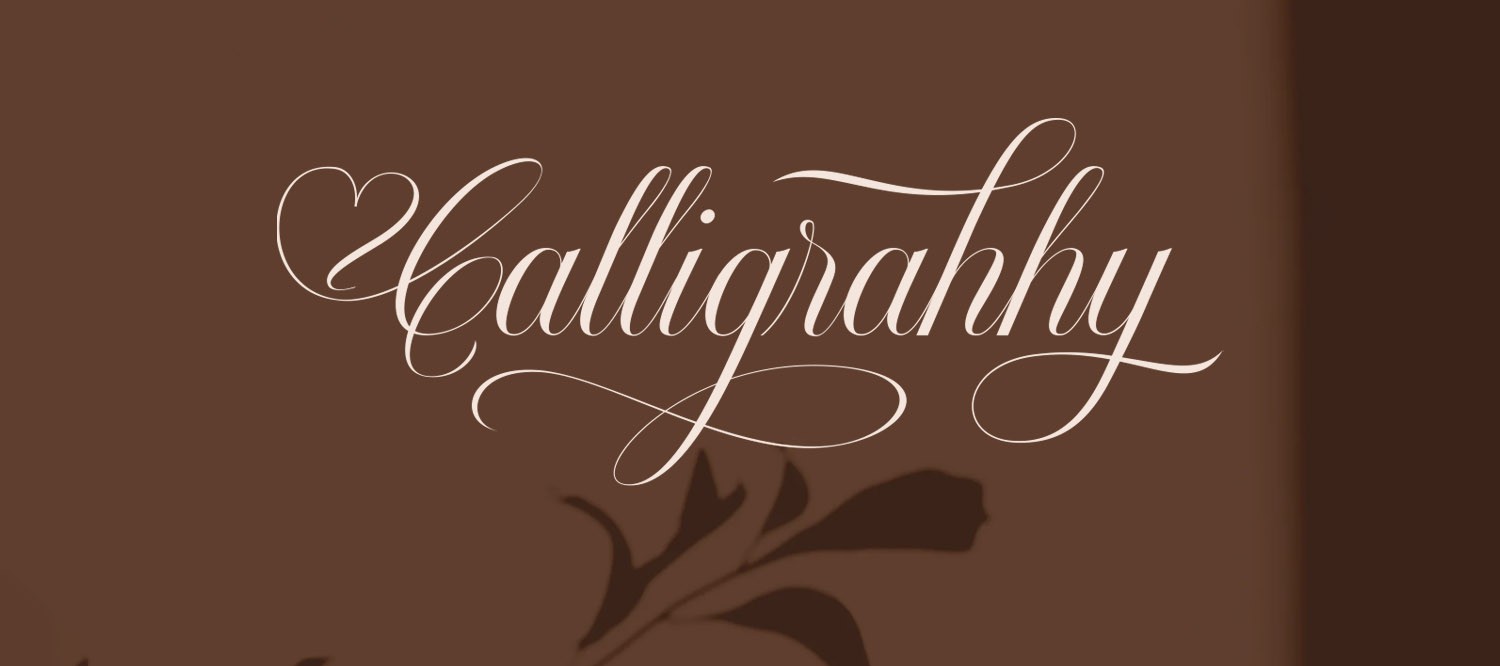
[Tải xuống] TOP 12+ font chữ calligraphy việt hóa mới nhất 2025
Trong lĩnh vực thiết kế, việc lựa chọn font chữ phù hợp đóng vai trò cực kỳ quan trọng trong việc thể hiện phong cách và cá tính của dự án. Font chữ Calligraphy, với nét chữ uốn lượn mềm mại, thanh thoát, là lựa chọn hoàn hảo cho những dự án cần sự tinh tế, trang nhã. Bài viết này sẽ giới thiệu đến bạn những font chữ Calligraphy đẹp mắt, phù hợp cho các dự án như thiệp cưới, thiệp mời, hay các ấn phẩm thiết kế sang trọng.
Font chữ Calligraphy là gì?
Font chữ Calligraphy (hay còn gọi là font chữ thư pháp) là một kiểu chữ được thiết kế để mô phỏng hoặc lấy cảm hứng từ các nét viết tay nghệ thuật, có sự uốn lượn và biến đổi mềm mại, linh hoạt của các nét chữ. Đây là một phong cách chữ truyền thống được dùng trong thư pháp, nơi người viết sử dụng bút lông hoặc bút chì mềm để tạo ra các chữ cái có độ dày mỏng khác nhau, mang tính thẩm mỹ cao và đầy nghệ thuật.
Top 12+ font chữ Calligraphy ấn tượng cho thiết kế
Với những đặc điểm nổi bật này, font chữ Calligraphy đã trở thành một công cụ thiết yếu trong thiết kế đồ họa, đặc biệt là khi bạn muốn mang đến cho sản phẩm của mình sự tinh tế và sang trọng.
Font chữ viết tay mềm mại SVN Nautica | Link tải
Font chữ SVN Nautica là một lựa chọn tuyệt vời cho những thiết kế cần sự mềm mại và thanh thoát. Được thiết kế với phong cách calligraphy hiện đại, SVN Nautica mang đến vẻ đẹp tựa như những nét vẽ tay, rất phù hợp với các thiệp mời, thiệp cưới hay thiết kế sự kiện sang trọng.
Font chữ viết tay lãng mạn Radja Lover Script | Link tải
Radja Lover Script là font chữ Calligraphy Việt hóa mang phong cách chữ ký uốn lượn mềm mại, đầy lãng mạn và tinh tế. Đi kèm với hơn 800 glyphs, bao gồm các glyph được thiết kế với hình trái tim độc đáo, đây là lựa chọn lý tưởng cho các thiết kế thiệp cưới, thiệp mời, hay các sản phẩm yêu cầu tính thẩm mỹ cao.
Font chữ mềm mại phong cách vintage TH Maryatha | Link tải
TH Maryatha là font chữ Calligraphy với phong cách vintage, mang đậm dấu ấn của những thập niên xưa cũ. Những nét chữ mềm mại và bay bổng với thiết kế dạng kiểu bằng bút chì màu của font này phù hợp với các thiết kế đậm chất cổ điển như thiệp mời vintage, thiệp cưới, hay các dự án yêu cầu sự tinh tế, nhẹ nhàng.
Font chữ viết tay chúc mừng năm mới FZ Christmas Carol | Link tải
FZ Christmas Carol là font chữ Calligraphy tuyệt đẹp, được thiết kế đặc biệt dành cho các dự án mùa lễ hội. Với kiểu chữ uốn lượn đầy nét duyên dáng, FZ Christmas Carol mang đến không khí lễ hội, vui tươi nhưng cũng không kém phần sang trọng. Font chữ này rất phù hợp cho việc thiết kế thiệp Giáng Sinh, thiệp mừng năm mới hay các sản phẩm quà tặng đặc biệt. Đặc biệt, FZ Christmas Carol có thể kết hợp với nhiều phong cách thiết kế khác nhau, mang lại hiệu ứng nổi bật và hấp dẫn.
Font chữ nghiêng mềm mại TH Buttain Regular | Link tải
TH Buttain Regular là một font chữ nghiêng với phong cách calligraphy mềm mại, thanh thoát và vô cùng dễ sử dụng. Font này phù hợp cho những thiết kế cần sự chuyên nghiệp nhưng vẫn mang lại vẻ đẹp mềm mại, dễ chịu. Các thiết kế thiệp cưới, thiệp mời hay các ấn phẩm truyền thông sẽ trở nên ấn tượng hơn rất nhiều khi sử dụng TH Buttain Regular. Font chữ này kết hợp giữa nét cổ điển và hiện đại, tạo ra những sản phẩm độc đáo và thu hút.
Font chữ viết tay SVN Peristiwa | Link tải
SVN Peristiwa là font chữ Calligraphy script với các nét uốn lượn mềm mại, tạo cảm giác thư thái và nhẹ nhàng. Phong cách thiết kế của SVN Peristiwa rất thích hợp cho các dự án yêu cầu sự tinh tế, như thiệp cưới, thiệp mời hay các sản phẩm quảng cáo cần sự sang trọng, lịch sự.
Font chữ viết tay, chữ ký mềm mại SVN Boutique Script | Link tải
SVN Boutique Script là một font chữ Calligraphy rất tinh tế và dễ thương, mang đến sự phá cách ấn tượng. Những nét chữ uốn lượn nhưng không kém phần mạnh mẽ của font này tạo ra một sự sang trọng đầy cảm xúc, chắc chắn sẽ làm cho các sản phẩm của bạn thêm phần ấn tượng và thu hút sự chú ý của người xem.
Font chữ thanh lịch TH Griffiths | Link tải
TH Griffiths là font chữ Calligraphy với những nét thanh thoát, thanh lịch và đầy quyến rũ. Được thiết kế dành riêng cho các dự án thiệp cưới, thiệp mời hay các sản phẩm thiết kế mang đậm phong cách cổ điển, sang trọng và đầy tinh tế. TH Griffiths với những đường nét mềm mại và thanh thoát chắc chắn sẽ tạo điểm nhấn đặc biệt cho các sản phẩm thiết kế của bạn.
Font chữ ký viết tay TH Molahesta Italic | Link tải
TH Molahesta Italic là font chữ Calligraphy mang đậm phong cách chữ ký thanh thoát, uốn lượn mềm mại. Đây là lựa chọn hoàn hảo cho các thiết kế cần sự lãng mạn, nhẹ nhàng nhưng đầy tinh tế. Font chữ này thường được sử dụng trong các thiệp cưới, thiệp mời, hay các sản phẩm đậm chất nghệ thuật. TH Molahesta Italic giúp tạo nên một ấn phẩm mang đậm dấu ấn cá nhân, nổi bật và đầy cảm xúc.